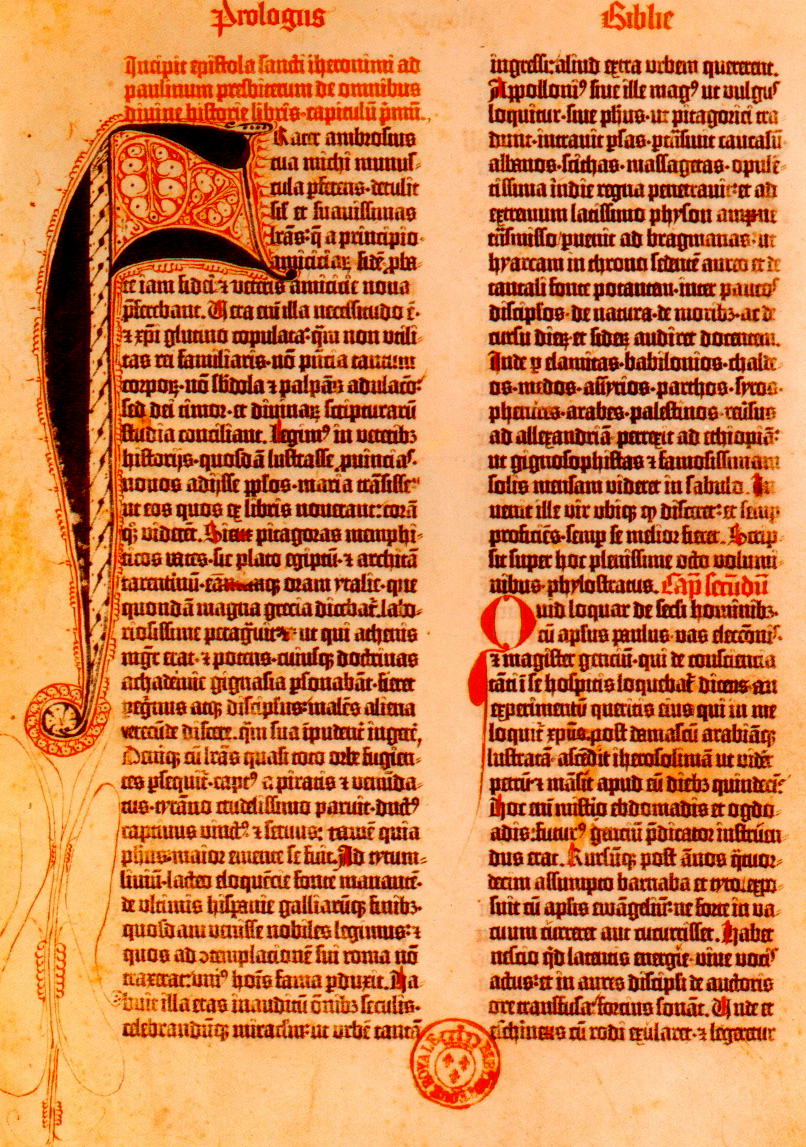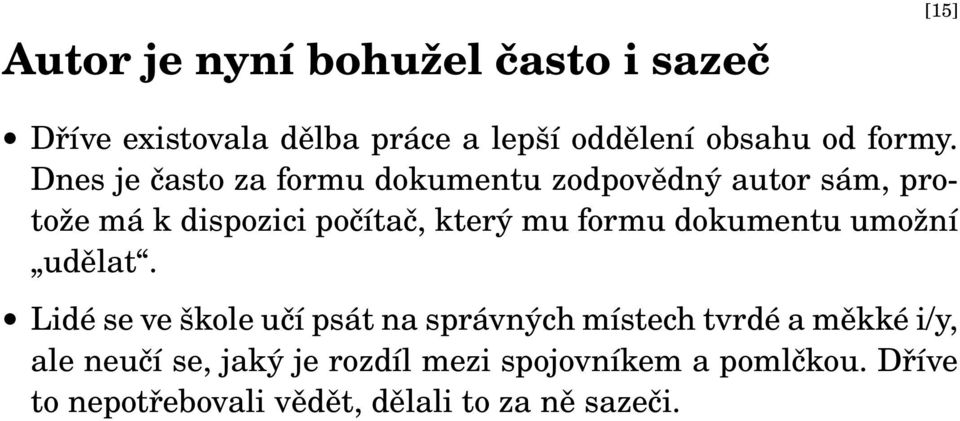
[1] Typografie.
1 [1] Typografie
2 Co je typografie? [2] Forma informací zaznamenaných pomocí písma zejména v případě tisku a při prezentaci na počítačích. Je na pomezí mezi řemeslem a uměním. Jiné vymezení: Typografie = grafická úprava tiskovin. Slovo je odvozeno z řeckého typós (znaky) + graphein (psát). Znaky byly za rozkvětu říše Římské tesány do kamene. Slovo typos má i tento význam.
3 Dobrá typografie? [3] Není vidět. Je nerušivým nástrojem ke sdělení obsahu informace. Ctí nejdůležitější pravidlo: čitelnost. Čtenář nesmí být unavován ani rušen. Podřizuje se staletým tradicím. Jen u některých akcidenčních tiskovin může v rozumné míře typografie vyčnívat. Pak se blíží užitnému umění. Jak rozpoznat kýč od umění? Neexistuje algoritmus. Jděte do galerií na Picassa, Botticelliho, Dalího, Dürera, Gaugina, Gogha, Alše, Špálu,... Nasajte atmosféru, nechte to do sebe absorbovat všemi smysly. Po mnoha letech pak poznáte rozdíl mezi kýčem a uměním, ale také to nebudete umět pojmenovat.
4 Mezníky v historii [4] Řeč (????? př. n. l.) Písmo (cca 4000 let př. n. l.) Mezopotámie, Sumerové, Akkadové, dále Egypťané, Féničané, Řekové, Římané,... Papír (105 n. l.) Čína, Čchan-Lun. V Evropě výrazně později Knihtisk (1440) Německo: Gutenberg, Nizozemí: Coster, Francie: Waldvogel Tisk z plochy, litografie Alois Senefelder (1800), výrazně později: forma připravená fotochemicky, ofset (1905). Rotačky, válec proti válci (1866) pro deník Times Fotosazba, osvit tiskové formy z filmů (1960) Počítače linotypy řízené strojem (1960), TEX (1979), Post- Script, PageMaker 1.0 (1985), počítač pro každého (1990),...
5 Technologie knihtisku [5] Tisk z výšky Jednotlivé litery (rozkládací/skládaci forma) Razníky, matrice Slévadlo: odlévaní liter matrice Tavitelná slitina: olovo, antimon, cín Vylepšení složení tiskové barvy: saze, oleje Tiskařský lis inspirován vinařským lisem
6 [6] 42řádková bible
7 Litera písmová kuželka [7] Výška sazby: normalizovaná na 23,55 mm Noha + zrcadlově obrácený reliéf písmene Stupeň písma: shodný pro celou písmovou sadu Šířka litery: proměnlivá Výplňkový materiál: čtverčík, půlčtverčík, třetina, osmina Kerning pomocí pilníku, kousků filmu atd.
8 Míry v typografii [8] Tyto míry byly používány dříve, než vznikl metrický systém. Bylo podle nich odlito velké množství písma, typografové se metrickému systému nepřizpůsobili. Princip: stopa = 12 palců, palec = 12 čárek, čárka = 6 bodů, tj. palec je roven 72 bodům. Jenže stopy byly různě veliké... Didotův bod v kontinentální Evropě vychází z francouzské stopy = 32,48 cm, bod = 0,367 mm, dvanáct bodů = cicero. Anglosaský systém, anglická stopa = 30,47 cm, bod (point) = = 0,351 mm, dvanáct bodů = pica. Ve výpočtu vznikly jakési zaokrouhlovací chyby. Současný americký palec (25,4 mm) má bohužel 72,27 anglosaských pointů. Proto Adobe zavedla počítačový bod = 1/72 palce = = 0,353 mm, dvanáct bodů = pica. Dnes nejpoužívanější systém.
9 Názvy stupňů písma (Didot, Fournier) [9] 6 bodů nonpareille 7 bodů kolonel 8 bodů petit (typicky pro poznámky pod čarou) 9 bodů borgis 10 bodů garamond (nejčastěji používaný stupeň) 11 bodů breviář 12 bodů cicero (podle Didotova bodu), pica (podle pointu) 14 bodů střední 16 bodů tercie 20 bodů text
10 Vývoj tiskového písma [10] Gotická textura: Gutenberg 1440 Dynamická (renesanční) antikva: Nicolas Jenson (1470), dnes písmo Centaur, Adobe Jenson První kurzíva (italika): Aldus Manutius, Francesco Griffo 1500 Další typografové renesance: Claude Garamond ( ), Christoph Plantin ( ), Wiliam Caslon ( ) Přechodová (barokní) antikva: John Baskerville (1754) Statická (klasicistní) antikva: Firmin Didot (1783) 19. století: písma pro plakát různé kvality. Stanley Morison: Times Roman Bezserifová písma: statická (Helvetica, Univers), dynamická (Gill), geometricky konstruovaná (Futura).
11 Jenson [11]
12 Francesco Griffo [12]
13 Klasifikace písma [13]
14 Co přinesly počítače? [14] Každý (často laik) má pod rukama sazárnu. Dříve byla sazba řemeslo, řemeslníci byli vyučeni v oboru. Řemeslo mnohdy ztratilo návaznost: typicky kdo uměl s počítačem neuměl původní řemeslo a obráceně. Bývalé oborové normy a ČSN vyšuměly do ztracena. Staré postupy práce přestaly existovat. Počítače přinášejí obrovské množství nových technologických možností: kerning, tisk přes sebe, barvy, písmo implementované pomocí beziérových křivek připraveno ke snadné transformaci, algoritmy a automatizace zlomu sazby, okamžité náhledy, kontrolní tisky na laserových tiskárnách,... Výtvarníci a odborníci mají možnost nové technologie využít. Je třeba to nepřehnat s kreativitou. Nelze čtenáře překvapit něčím jiným, na co nebyl zvyklý.
15 Autor je nyní bohužel často i sazeč [15] Dříve existovala dělba práce a lepší oddělení obsahu od formy. Dnes je často za formu dokumentu zodpovědný autor sám, protože má k dispozici počítač, který mu formu dokumentu umožní udělat. Lidé se ve škole učí psát na správných místech tvrdé a měkké i/y, ale neučí se, jaký je rozdíl mezi spojovníkem a pomlčkou. Dříve to nepotřebovali vědět, dělali to za ně sazeči.
16 Mikrotypografická pravidla [16] Dříve byla tato pravidla zahrnuta do ON , ta přestala platit v roce Dnes je možné použít ČSN Spojovník (-) Propan-butan, dělení slov, zvádne-li to sám, ISBN , slovník česko-anglický. Pomlčka na čtverčík ( ) a na půlčtverčík ( ) Chceme-li oddělit části věty od jiné části věty. Kratší pomlčka ve významu až, nebo dálnice Praha Brno. V těchto případech bez mezer kolem. Další vodorovné čárky : mínus a podtržítko. Třeba ve vzorci a 2 b 2 je první minus unární (bez mezery) a druhé minus binární (s malými mezerami z obou stran). Podtržítko se nepoužívá.
17 Tečky čárky, středníky. Nemají před sebou mezeru, za sebou mezeru mají. Otazník, vykřičník, dvojtečka mají před sebou vlasovou mezeru (nedělitelnou) nebo (není-li k dispozici) nemají před sebou mezeru žádnou. Závorky nemají zevnitř mezeru, z vnějšku ano. Sazba data nebo 23. května (Všimněte si mezer za tečkami, lidé je tam často nedávají!) Interpunkce pro konec věty je v závorce, pokud je v závorce celá věta (viz předchozí závorka), jinak je čárka a tečka až za závorkou (jako zde). I ve zkratce s. r. o. jsou mezery za tečkami, ale zúžené. Výpustka neboli elipsa (... ) má často ve fontu svůj obraz, když ne, pak musí být vhodně vzdušná... Samotné tři tečky vedle sebe jsou často nevhodně natlačeny na sebe..., takže to by se vyskytovat nemělo. Výpustka na konci věty nemá za sebou čtvrtou tečku. [17]